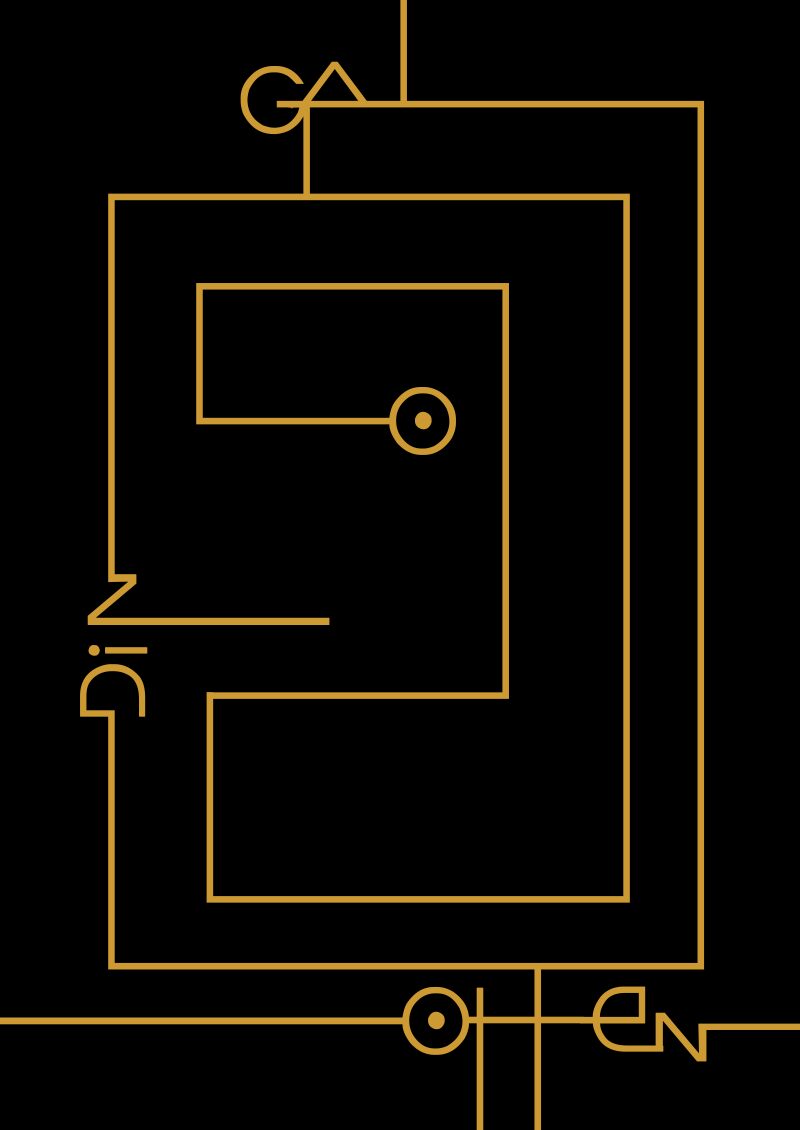
Stretched Signature Ext Bold Italic
Stretched Signature Ext Bold Italic, zaprojektowany przez Galdino Ottena, to darmowy krój pismowy typu techno display o szerokich, wyrazistych kształtach liter. Zaokrąglone zewnętrzne krzywizny łączą się z kwadratowymi cięciami i nagłymi łączeniami, nadając literom profil o maszynowym charakterze. Formy są gęste i mocno uproszczone.
Kultura cyfrowa i motywy retrofuturystyczne łączą go z interfejsami gier, plakatami muzyki elektronicznej oraz grafiką imprez science-fiction. Jego kanciaste kształty mogą stać się częścią emblematu inspirowanego obwodami elektronicznymi lub nagłówka na opakowaniach produktów technologicznych. Krój jest szczególnie odpowiedni dla projektantów zwracających się do odbiorców z branży gier, klubowej i technologii użytkowej.
This font was conceived according my self signature that you can see in all my artwork in my blog as well street art writings, and the it can be used in diverses ways and artstylles, it can be used of the simplest the most sophisticated work until. Its more important characteristic is the flexibility of its connections, for being linked becomes infinitely flexible being able to transpose the limitations of any space.